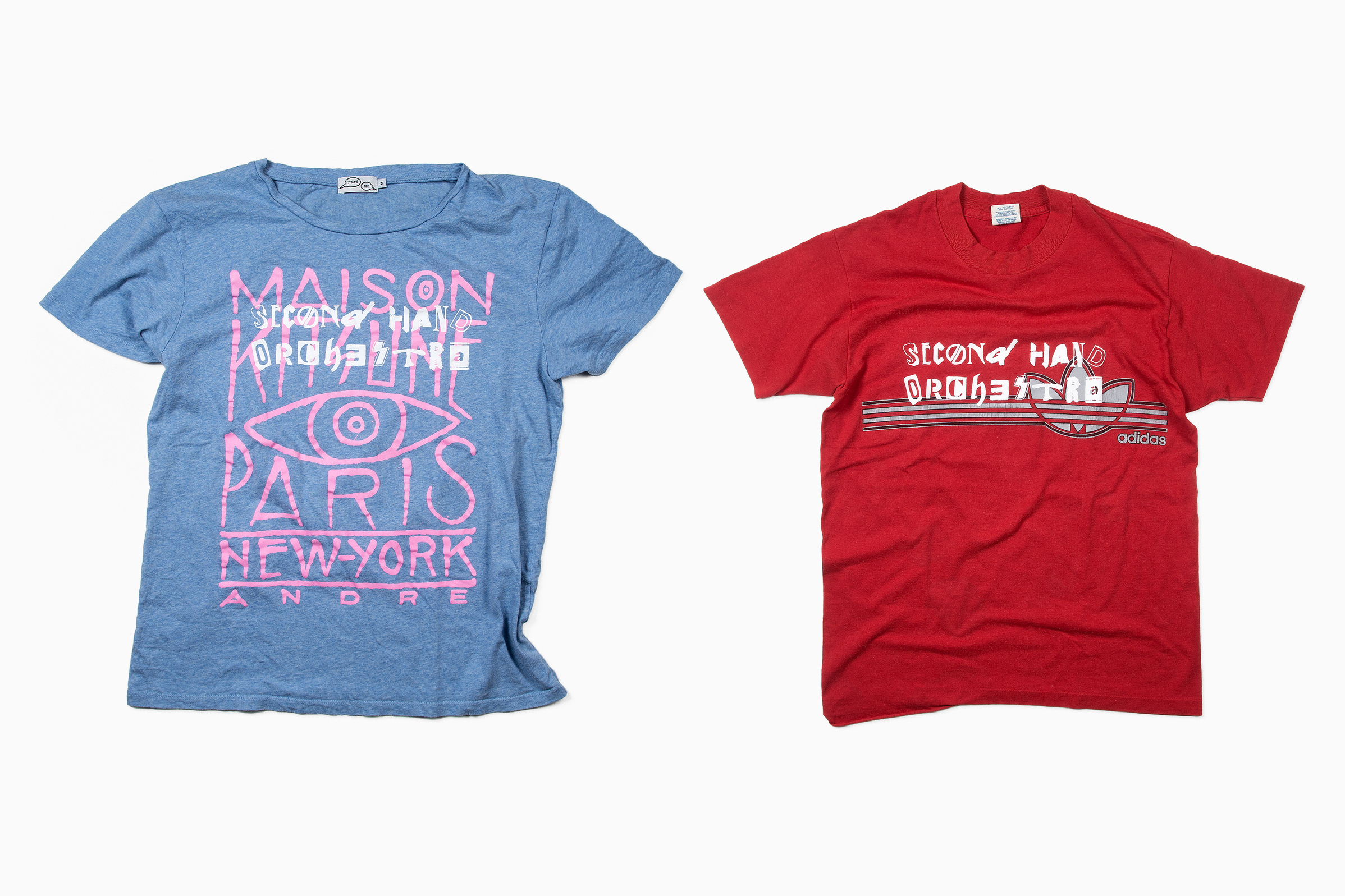
Projektet lades ner efter ett år när regissören försvann utan ett ord. Kvar fanns en obetald orkester med en handfull låtar utan sammanhang – det var då bandledaren Karl-Jonas Winqvist valde att återvinna projektet. Musiken som skapades skulle ges ut på skiva istället, under namnet Second Hand Orchestra.
Återvinningsidén fortsatte när designbyrån Bedow kopplades in.
– Vi har försökt omsätta ”second hand” till design i så stor utsträckning som möjligt. Logotypen består av återanvända logotyper, vi har gjort skivomslag av befintliga LP-omslag och vi har återanvänt t-shirts som vi har tryckt bandets logotyp över, säger Anders Bollman som är designer på Bedow.
Hur valde ni vilka bandnamn ni skulle använda till logotypens bokstäver?
– Vi ville använda oss av internationella artister och blanda kända logotyper som Kiss och Eminem med mindre kända band som Devo och Cramps. Det måste också finnas en karaktär i logotyperna, det vore ganska ointressant att ta ett helt okänt band eller en artist som har satt sin logotyp i en generisk sans-serif. Av någon anledning så var det mest hårdrock och hip-hop som hade en tydligare identitet. Det var också svårt att hitta kvinnliga artister med en karaktäristisk logotyp.
Finns det några frågor kring copyright när det kommer till att återanvända material på det här sättet?
– Schhh… Nej, skämt åsido så har vi svårt att se att någon skulle ta illa upp. Dels så är det en liten upplaga på endast trehundra skivor och dessutom är bokstäverna handtecknade vilket göra att de inte är helt identiska med originalen.